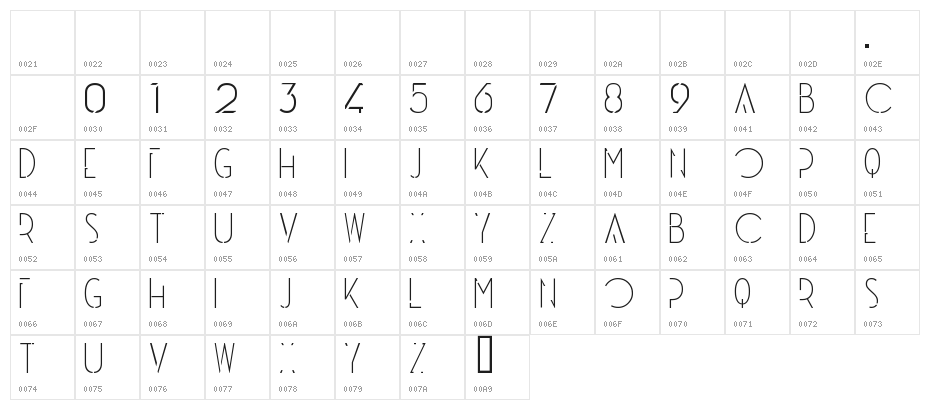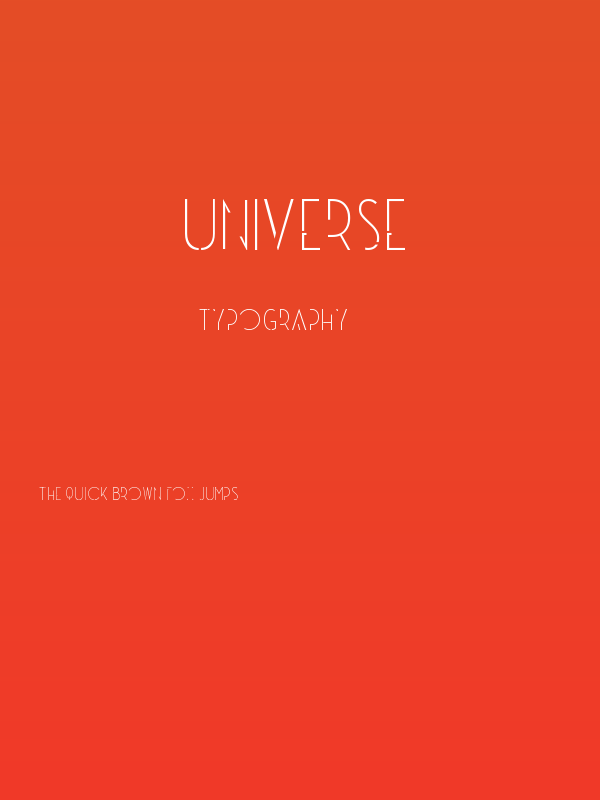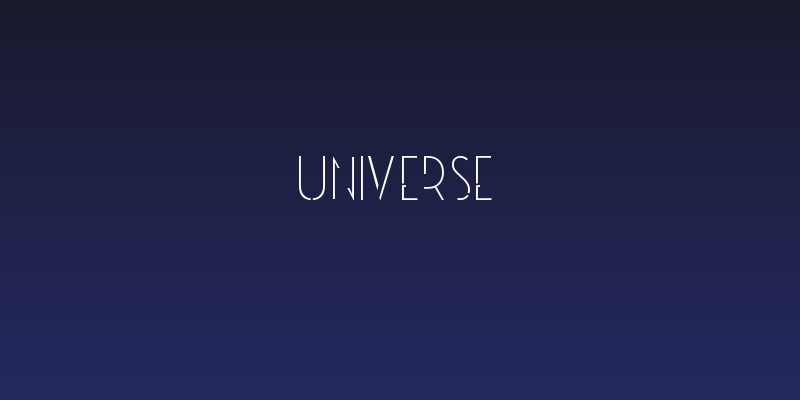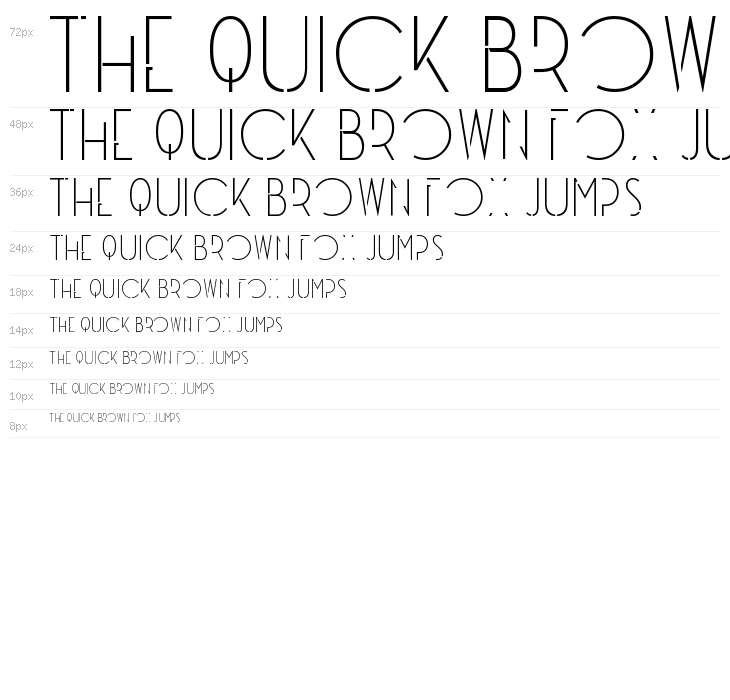
Universe Font
| 分类 | Hi-tech |
| 整体风格 | Futuristic, Geometric |
| 使用场景 | Headlines, Logos, Branding |
| 推荐项目 | Ideal for technology branding, sci-fi themes, modern advertising, and innovative design projects. |